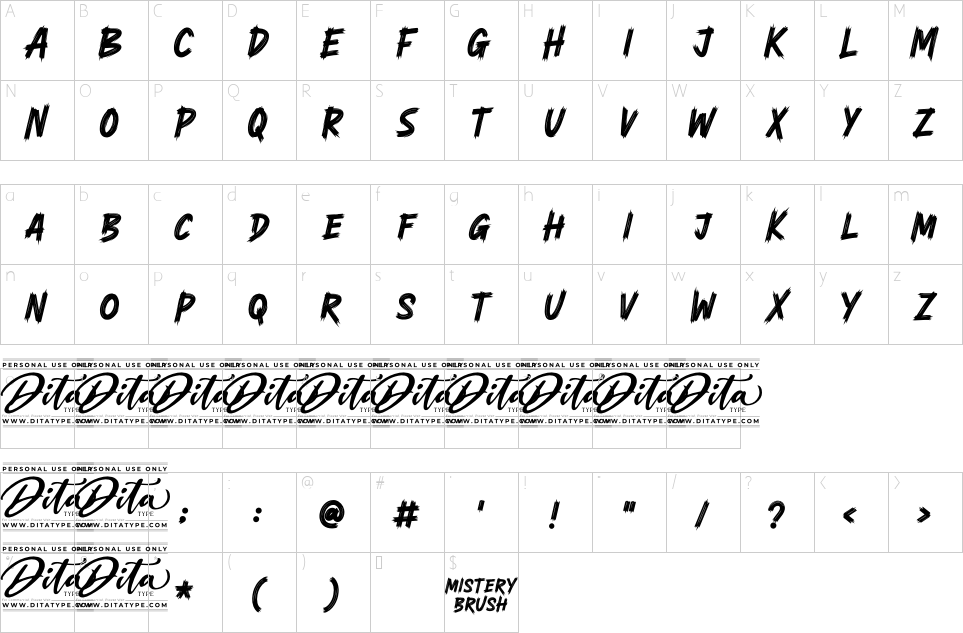
A fonte Mistery Brush é uma opção divertida e autêntica para aqueles que buscam algo diferente para seus projetos digitais. Desenvolvida pela Dita Type, essa fonte está disponível gratuitamente tanto para sistemas Windows quanto Mac. Mistery Brush traz um toque único e criativo às suas criações, tornando-a uma escolha atraente para designers e ilustradores. Com sua design simples e eficaz, Mistery Brush pode ser usada em uma variedade de aplicativos, desde criações gráficas e logotipos até design de sites e e-mail personalizados. Mais de 2.993 pessoas já aprovaram seu uso, o que significa que ela deve ser uma excelente opção para qualquer projeto que busque uma sensação única e diversificada. Descubra por si mesmo o encanto desta fonte única e descarregue Mistery Brush hoje.